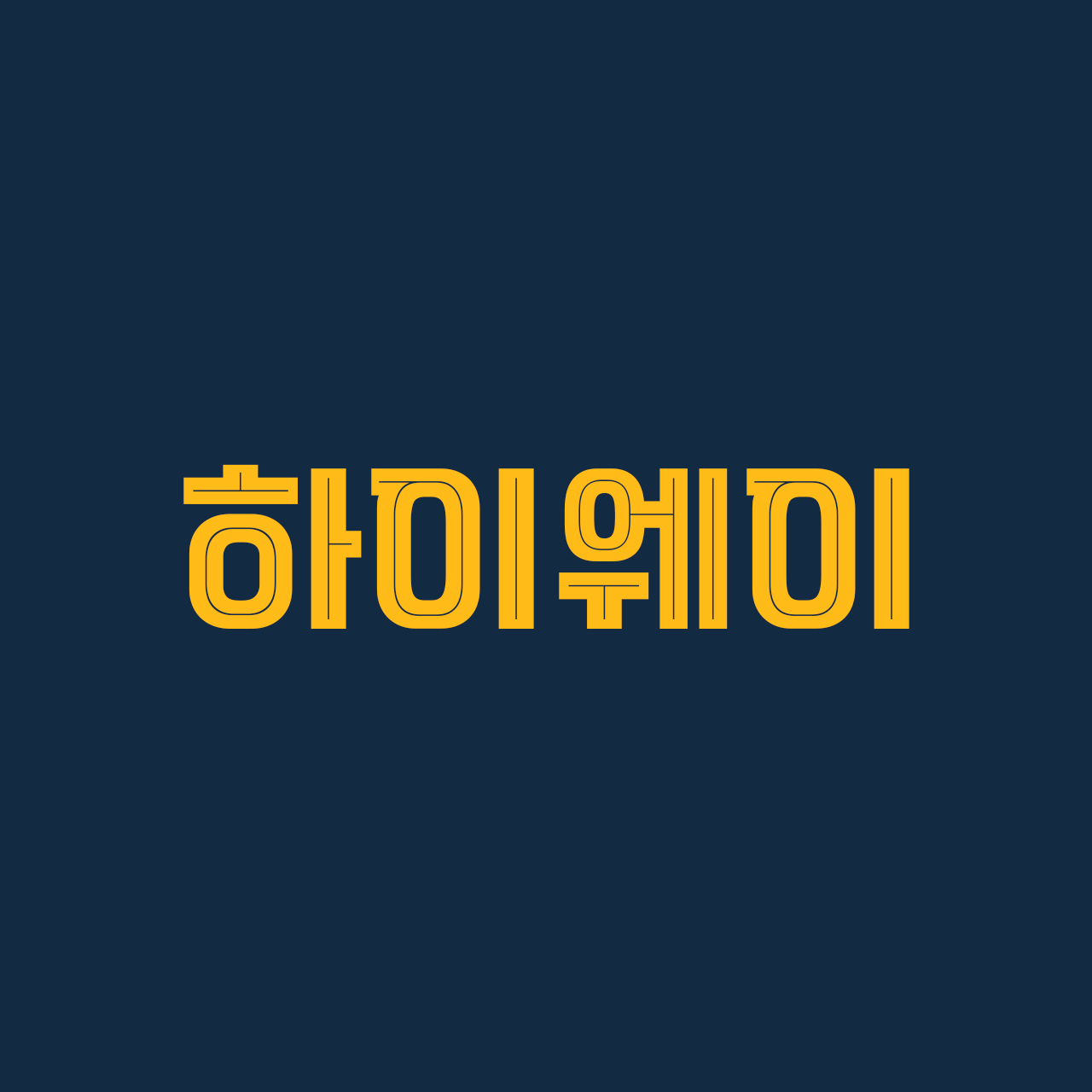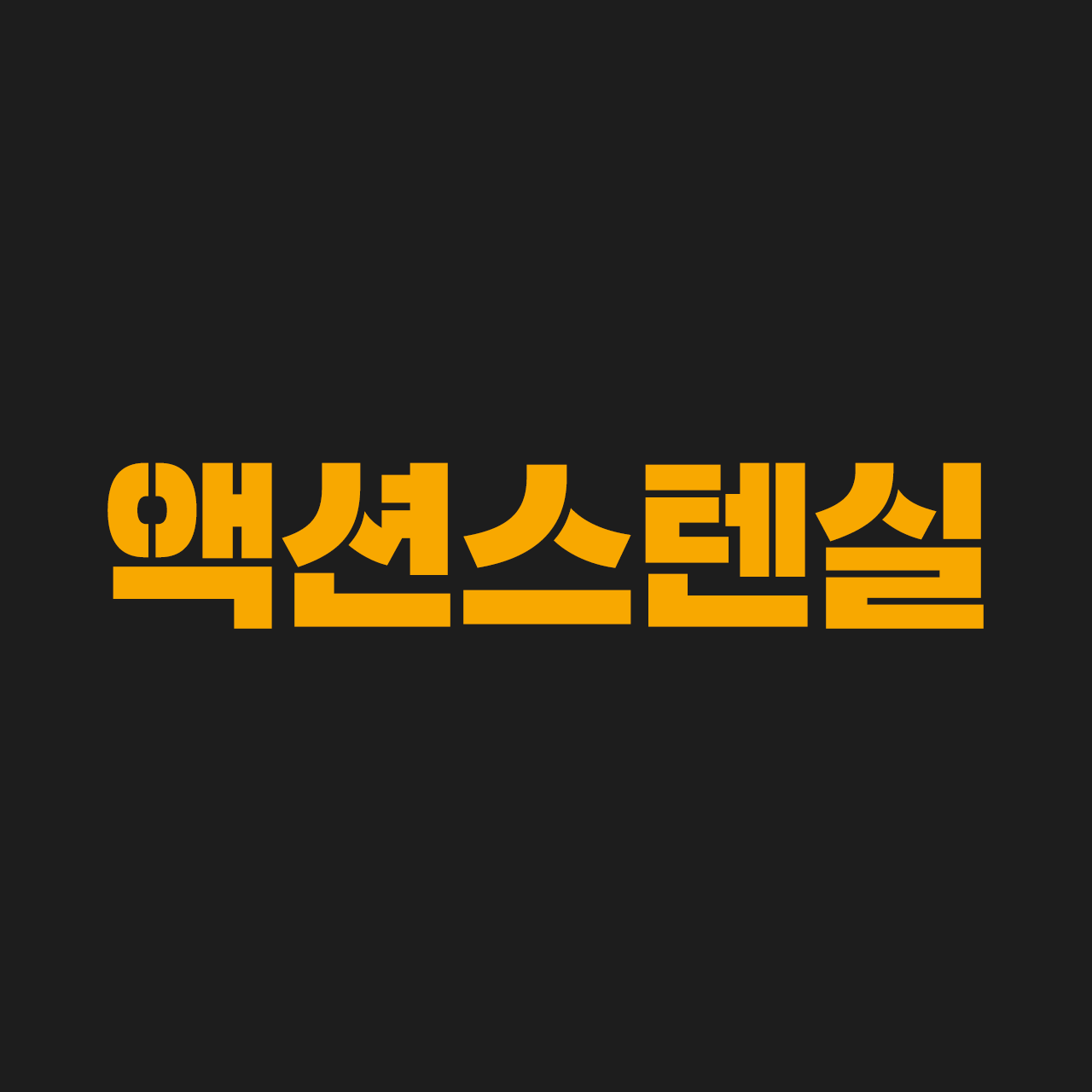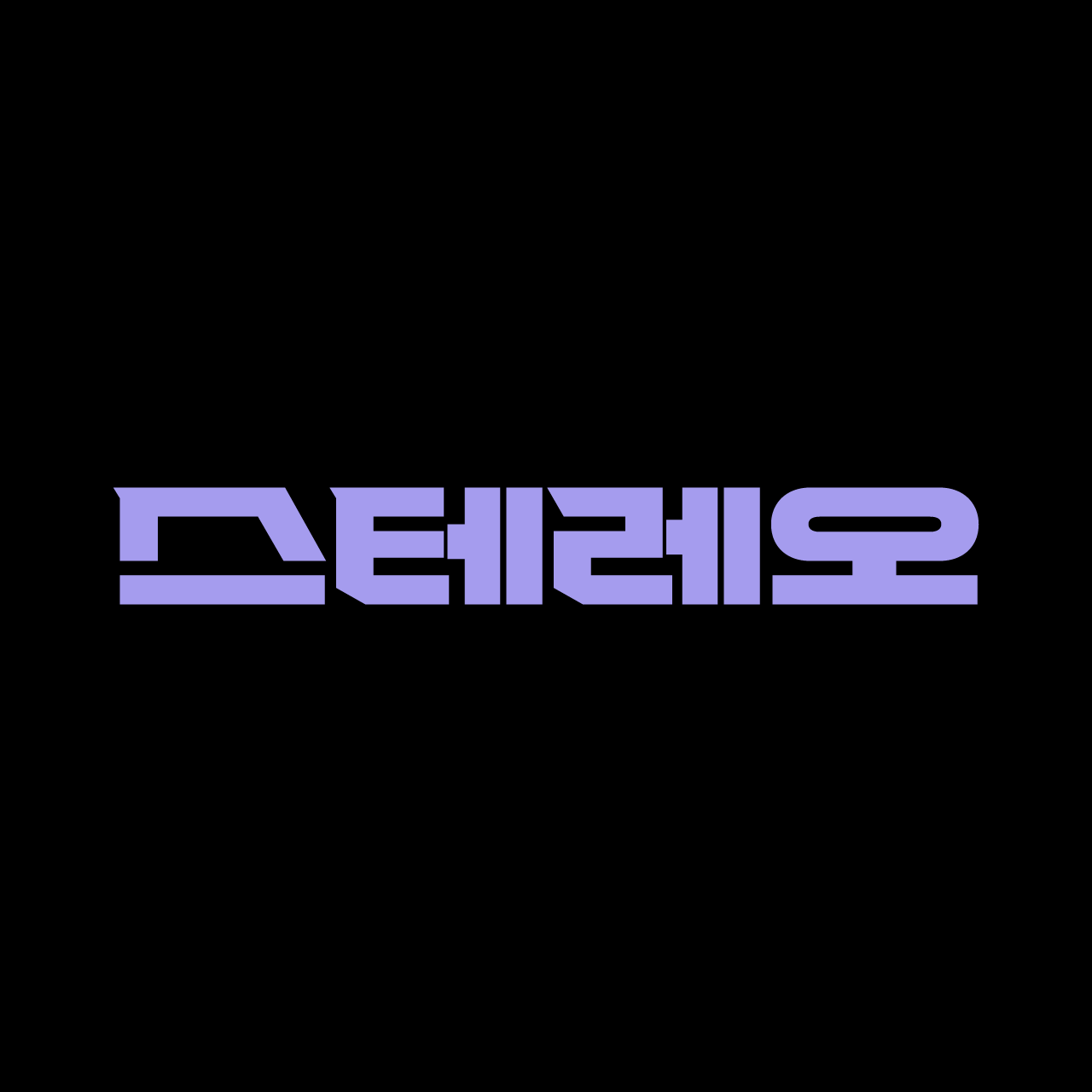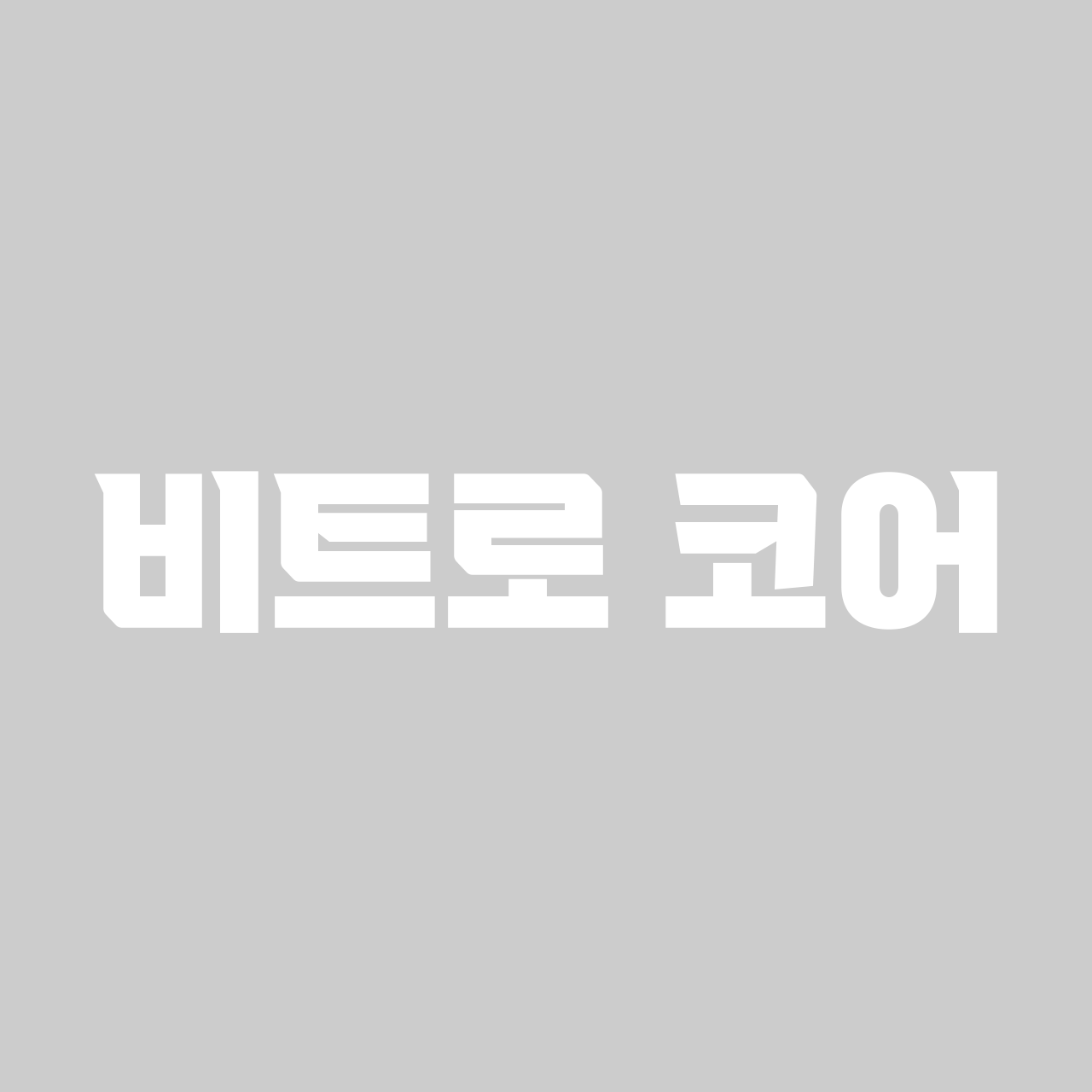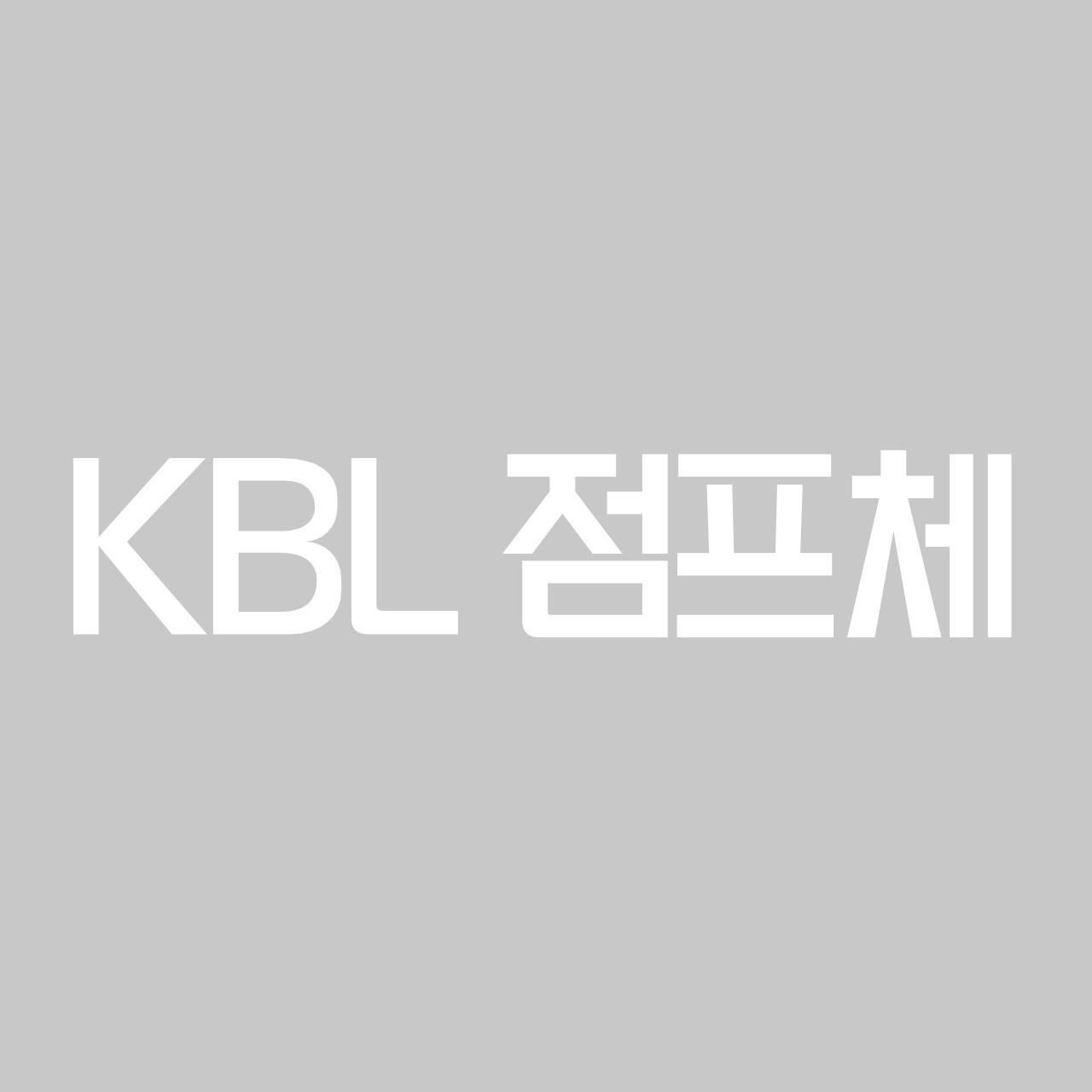
우리는 디자인을 할 때 '힘, 에너지, 시원시원함'을 표현해야 하는 순간을 자주 마주하곤 합니다. 이럴 때 굳이 화려한 그래픽 효과를 넣지 않더라도, 폰트 하나만 잘 고르면 원하는 느낌을 100% 전달할 수 있다는 사실, 알고 계셨나요?
그렇다면 힘이 넘치고 당장이라도 액션을 취할 것 같은 강인한 인상을 주려면 폰트에 어떤 속성이 있어야 할까요? 지금부터 그 비밀을 하나씩 알아보겠습니다.
보통의 한글 폰트는 기본 네모꼴 안에 그려지기 때문에 정사각형이나 조금 날씬한 직사각형 형태를 띱니다. 하지만 이 틀을 깨고 옆으로 쭉 늘린 서체들이 있습니다. 라틴 서체(영문 폰트)에서는 이런 스타일을 'Extended(익스텐디드)'라고 부르는데요. '확장된', '넓어진'이라는 뜻으로, 글자의 가로 폭을 넓혀 시각적인 무게감과 안정감을 극대화한 서체 스타일을 말합니다.
대표적으로 「KBL 점프체」가 이러한 넓은 특성을 가지고 있습니다. 가로로 시원하게 뻗은 구조 덕분에 전체적으로 스포티하고 에너제틱한 느낌을 주며, 멀리서도 눈에 확 들어오는 강렬한 주목성을 자랑합니다.
한글 디자인에서 '시옷(ㅅ), 지읒(ㅈ), 치읓(ㅊ)'은 대각선 획이 중심이 되기 때문에 시각적으로 눈에 가장 많이 띄는 글자입니다. 특히 이 '시옷'의 모양을 어떻게 설계하느냐에 따라 폰트의 전체 인상이 완전히 달라지기도 합니다.
곡선 없이 직선으로 재미있고 시원하게 쭉쭉 뻗은 디자인의 폰트들을 소개합니다. 글자 자체에서 속도감과 거침없는 에너지가 느껴지지 않나요?
마지막으로, 꽉 찬 네모꼴 꽉찬 서체도 빠질 수 없습니다. 글자 면적을 꽉 채워 묵직한 한 방을 날리는 듯한 인상을 주는데요. 여기에 디테일이 더해지면 그 강인함은 배가 됩니다.
이번에는 스탬프를 쾅! 하고 찍은 것처럼 역동적인 느낌을 주는 「Sandoll 액션스텐실」의 Noisy 스타일을 추천합니다. 질감이 러프해서 날 것 그대로의 거친 에너지가 느껴지죠.
또 다른 매력의 「비트로 코어체」 역시 네모꼴을 꽉 채운 강인한 서체입니다. 이 서체는 세로획 끝에 달린 날카롭고 뾰족한 세리프(돌기) 디테일이 특징인데요, 이 섬세한 날카로움이 폰트의 강렬한 인상을 더욱 강력하게 만들어 줍니다.
지금까지 강력하고 힘 있는 인상을 만드는 폰트의 속성 3가지를 알아보았습니다.
다음에 파워풀하고 시원시원한 분위기의 디자인을 기획할 때, 이 3가지 포인트를 눈여겨보며 폰트를 골라보시는 건 어떨까요?